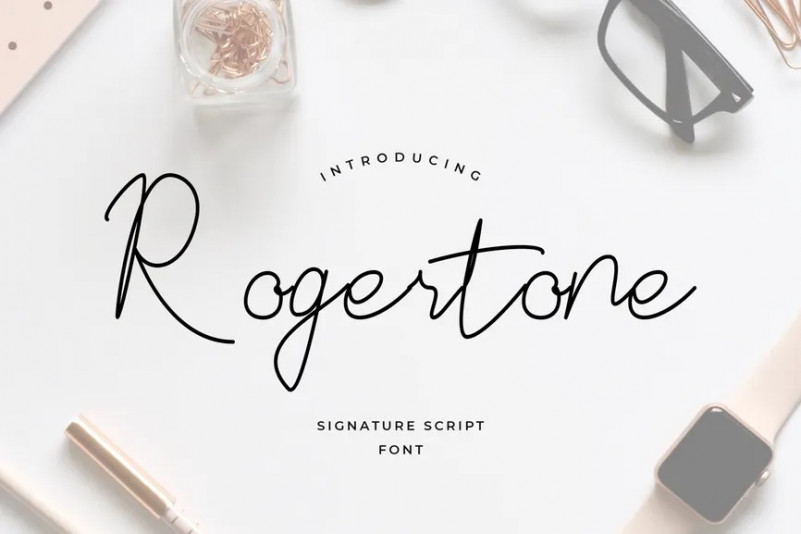
Rogertone Font
Rogertone est parfaite police Signature pour les projets de marque, Logo, dessins de mariage, messages de médias sociaux, publicités, emballage de produits, conceptions de produits, étiquette, photographie, filigrane, invitation, papeterie et tous les projets qui ont besoin de goût d’écriture manuscrite.
Cette police a un flux vraiment agréable donc vous l’utilisez dans un grand texte si vous voulez leur donner une touche de personnalité. Il peut être utilisé sur le contenu des médias sociaux, pour l’image de marque ou l’emballage.